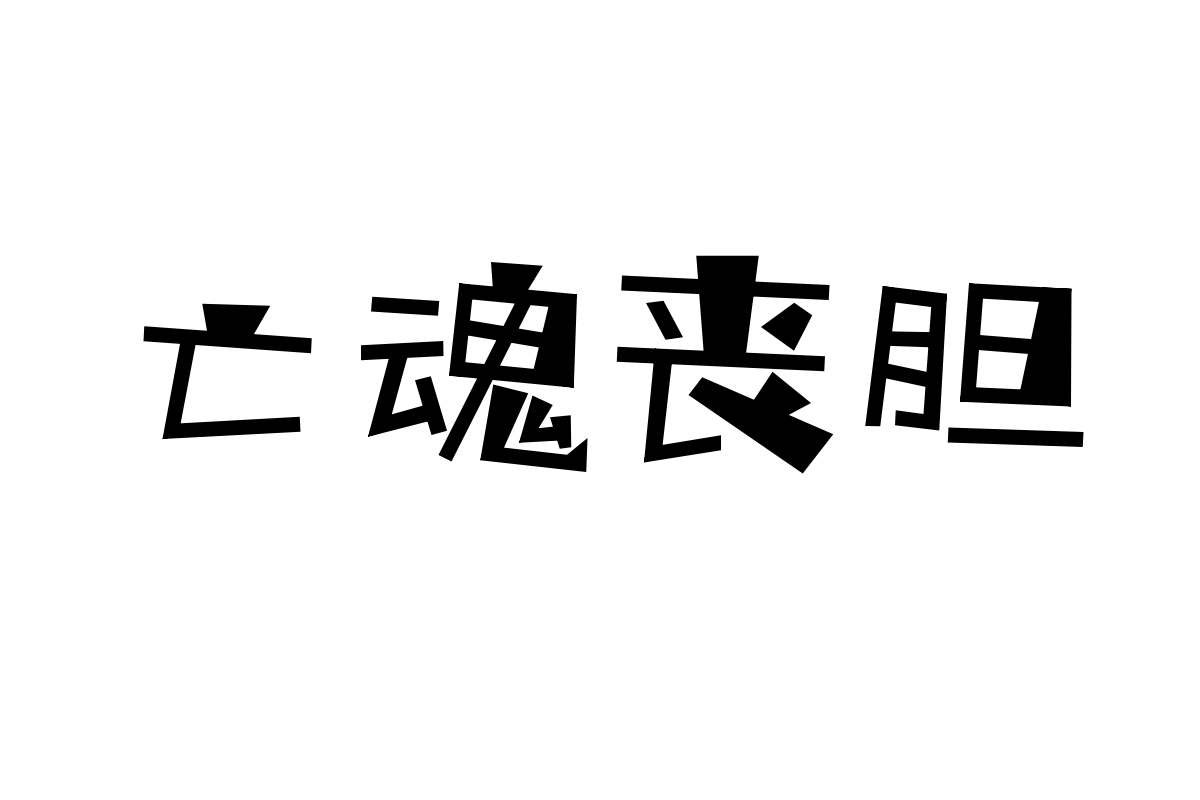
三极枫林字体是一种具有独特风格的中文简体字体,以其粗犷、有力的线条和独特的字形结构而闻名。这种字体的设计灵感来源于自然界中的枫树,通过将枫叶的轮廓和纹理融入到字体中,创造出一种既具有艺术感又具有实用性的独特字体。
三极枫林字体的特点包括:
1. 粗犷:字体线条粗犷有力,给人一种强烈的视觉冲击力。
2. 自然:字体的设计灵感来源于自然界中的枫树,通过将枫叶的轮廓和纹理融入到字体中,展现出一种与自然和谐共生的感觉。
3. 独特:字体的字形结构和笔画走向具有很高的辨识度,使得在众多简体字中能够脱颖而出。
4. 美观:虽然字体粗犷,但在实际使用中,其美观程度不亚于其他常见的简体字。
5. 易读性:字体设计注重易读性,使得在日常书写和阅读中能够快速识别和理解。
总之,三极枫林字体以其独特的风格和实用性,受到了广大设计师和用户的喜爱。